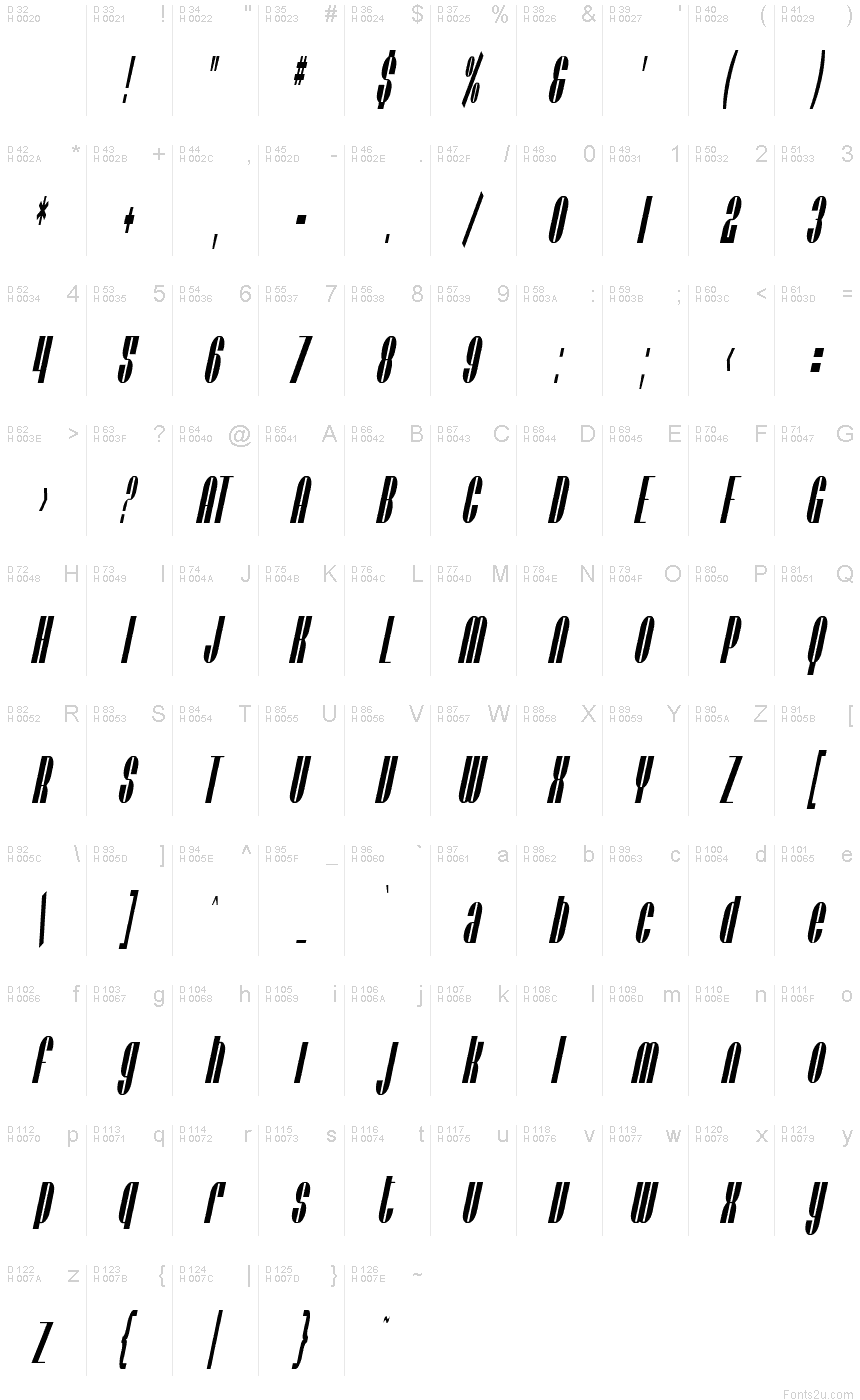
SF Baroquesque Oblique
SF Baroquesque od ShyFonts Type Foundry to darmowy, pochyły font typu display w stylu retro, z wyrazistym charakterem Art Déco. Litery są wysokie, kompaktowo nakreślone i mocno pochylone, a ścięte łuki oraz wąskie pionowe kreski nadają całemu projektowi dynamiczny rytm, niczym z dawnych plakatów.
Naturalnie odnajduje się w menu koktajlowych, ulotkach, okładkach płyt, szyldach sklepowych i tytułach filmowych, gdzie jej smukła sylwetka dodaje charakteru krótkim napisom. Jako darmowy font, świetnie sprawdzi się również w nagłówkach, cytatach i krótkich projektach brandingowych, które potrzebują odrobiny teatralnego, vintage'owego klimatu, nie popadając przy tym w przesadną dekoracyjność.